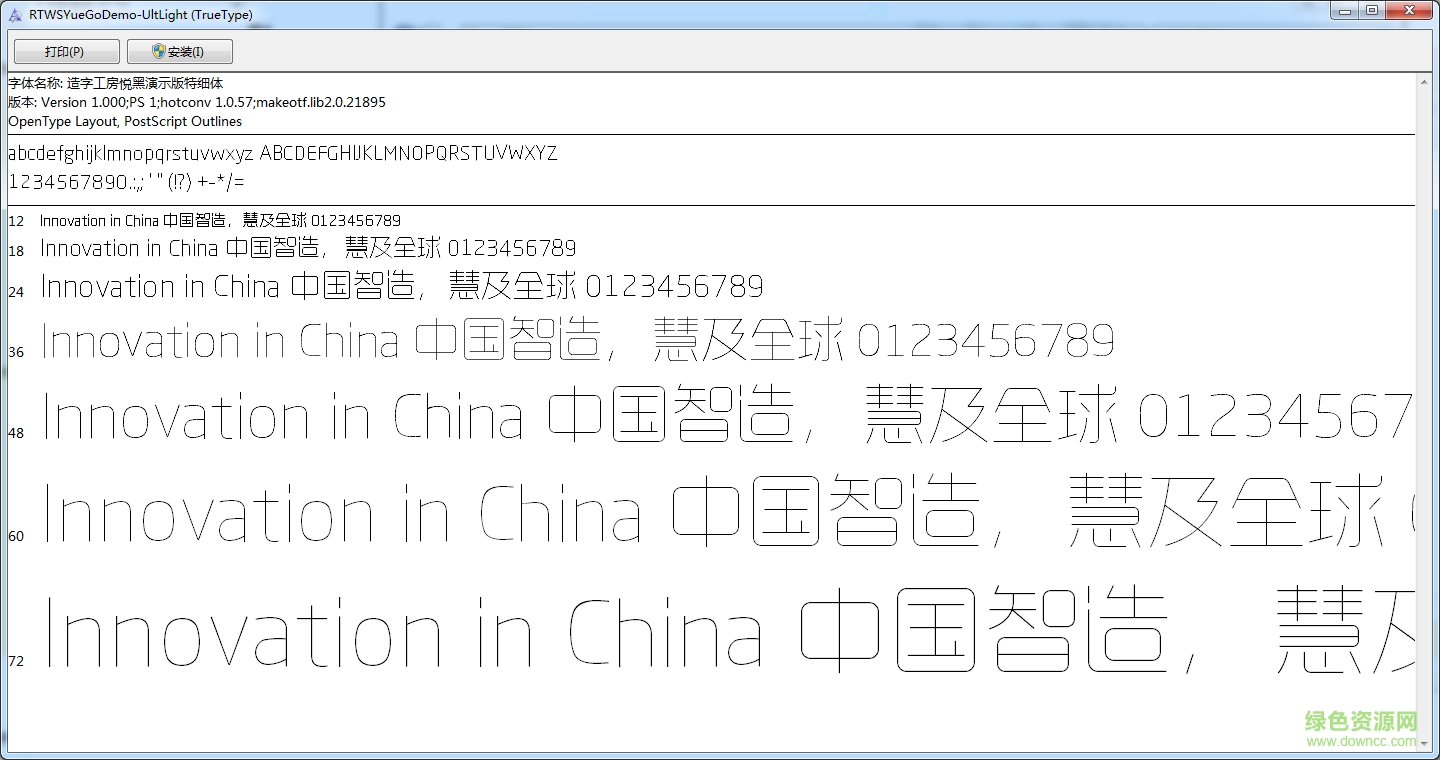
造字工房悅黑演示版細(xì)體
造字工房悅黑演示版特細(xì)體是一款簡(jiǎn)潔大氣的win細(xì)體,此款字體線條較細(xì),清醒爽目,擁有完整的字庫(kù),結(jié)構(gòu)簡(jiǎn)潔,易讀性強(qiáng),安裝簡(jiǎn)單方便,使用范圍非常廣泛,喜歡的朋友歡迎來綠色資源網(wǎng)下載!